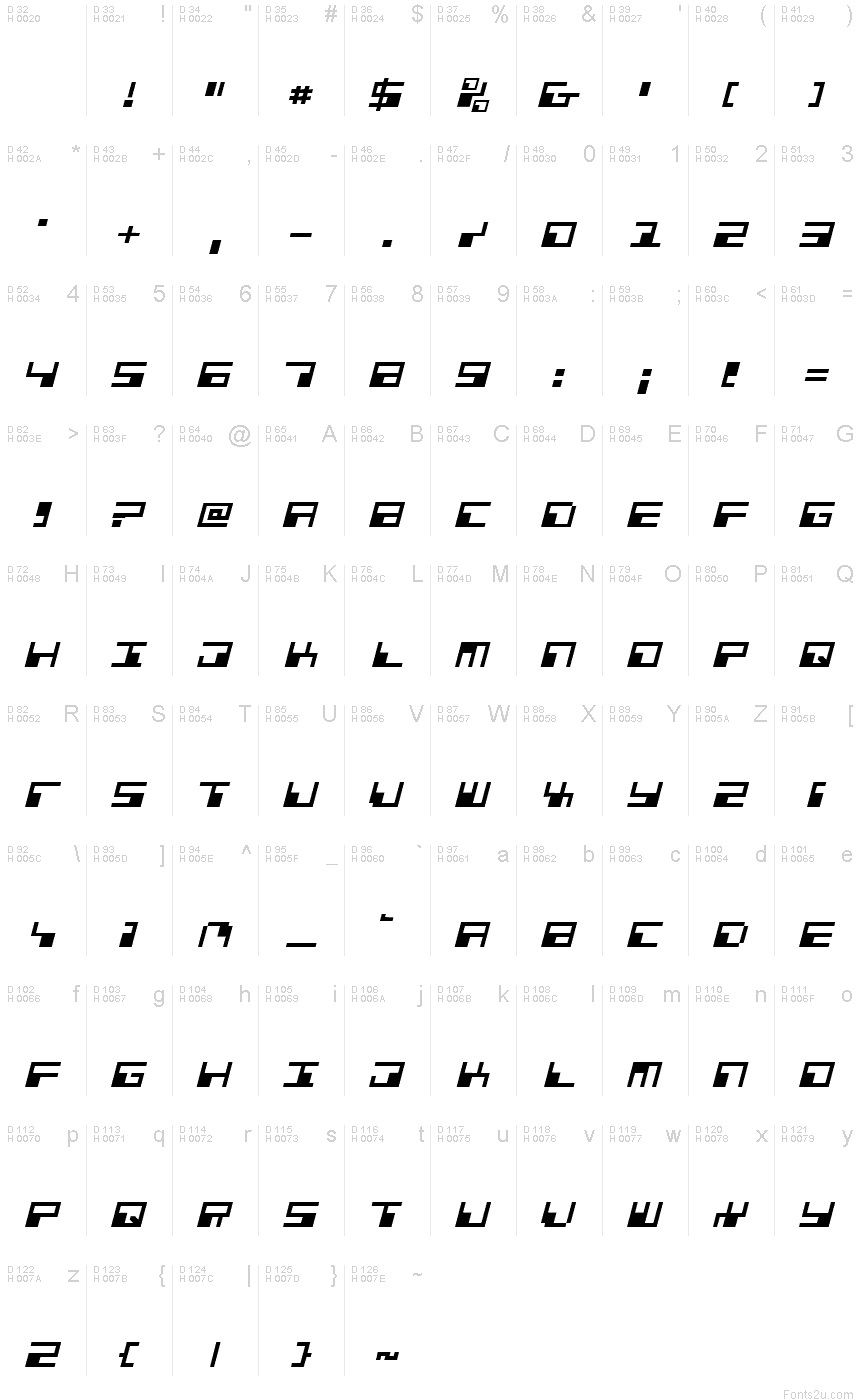
Phaser Bank Expanded Italic od Iconian Fonts to futurystyczny, techniczny krój pisma typu all-caps z szerokimi, pochylonymi literami i ostrymi cięciami. Kwadratowa konstrukcja, otwarte prześwity i ścięte rogi nadają mu szybki, inżynieryjny rytm, przywodzący na myśl interfejsy sci-fi i grafikę arcade.
Świetnie sprawdzi się w logotypach gier, plakatach, brandingu esportowym, okładkach albumów elektronicznych oraz tytułach. Najlepiej wygląda w krótkich frazach – szerokie proporcje i agresywne pochylenie nadają nagłówkom charakter wyścigowych emblematów lub oznaczeń statków kosmicznych.